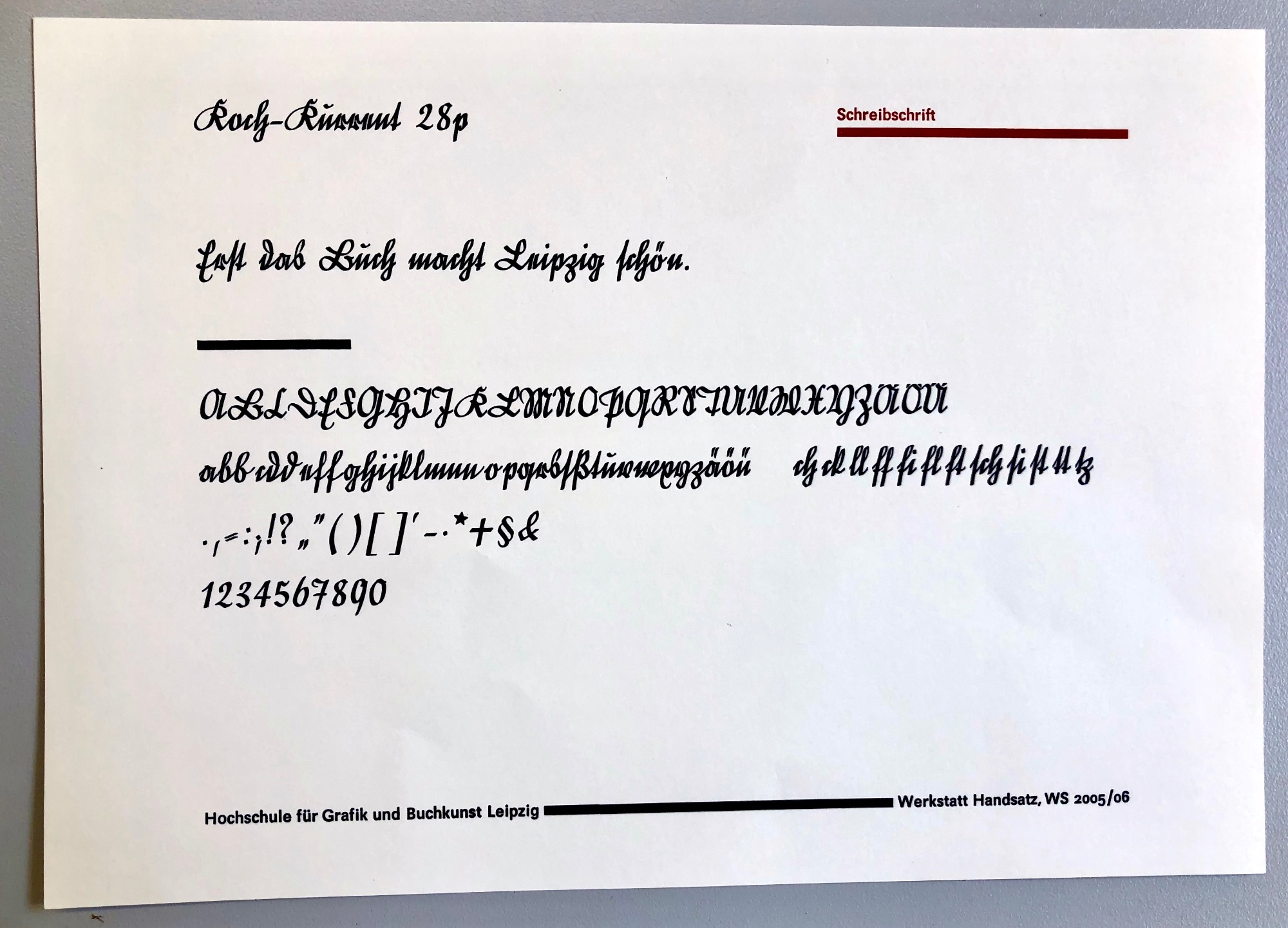
Nebenan: Kochs Kurrentschrift
Ich habe mir gerade Ralfs neuen Eintrag zur Koch-Kurrent von Rudolf Koch angesehen und dabei (freudig) festgestellt, wie viel Dynamik und »Charakter« die Schrift im Bleimuster [a] hat – und wie viel davon in der Digitalisierung [b] (wohl nur durch µ-weise Verschiebungen) verlorengegangen zu sein scheint. Das hatte für mich den Effekt, dass ich [a] sofort Lust aufs Kurrentlesen bekam, aber dann [b] – ruckzuck – auch wieder nicht.
Geht das nur mir so?
Naja, so eine schlampige Digitalisierung tut der Sache natürlich keinen Dienst. Die Verbindungen passen nicht; die Formen sind nurmehr durchgepaust. So geht alles Leben der Schrift verloren. Ein digitaler Abklatsch eben...
… umso mehr kann man wertschätzen, was für ein Kunsthandwerk doch die Matritzenschneiderei war.
Hallo. mein Name ist Iris Köhler. Ich bin gelernte Schriftsetzerin (wissenschaftlich-mathematischer Werksatz) und übe meinen Beruf mit Bleibuchstaben seit 49 Jahren aus. Acht Jahre bei INTERDRUCK und seit 41 Jahren in der Werkstatt Handsatz in der Hochschule für Grafik und Buchkunst Leipzig. Dies nur zur Vorgeschichte, damit Sie wissen, warum ich mich so gut auskenne.
Wir haben hier ein unserer Werkstatt 146 Bleischriften, u.a. auch die Koch-Kurrent. Ich liebe diese Schrift sehr. Hier ein Foto von dieser Schrift aus unserer Schriftmuster-Kartei.
Kleine Anmerkung: War es nicht eher so: Die Matrize wurde geschlagen, geschnitten hat der Stempelschneider die Patrize? Aber in der Tat, als Kunsthandwerk beeindruckend.
Der Großteil von Klingspor-Schriften entstanden wahrscheinlich im Zeugschnitt anstelle vom Stahlstempel. Die Patrizen waren wohl von Hand des Stempelschneiders geschnitten, jedoch war ein Metall verwendet, was weicher als Stahl war. Matrizen bzw. Matern waren dann nicht geschlagen. Stattdessen entstanden deren »Augen« im galvanischen Bad. Gelegentlich sind Matrizen bei Gebr. Klingspor auch direkt in Matrizen eingraviert worden, mittels einer Pantograf-Bohrmaschine. Rudolf Koch bzw. seines Sohnes Paul Koch (und Gustav Eichenauer etwas weniger wahrscheinlich) haben mehrere Schriften direkt in Stahl geschnitten. Das war damals schon eher alte Schule. David M. MacMillan haltet es für wahrscheinlich, dass Neuland zumindest zum Teil von Koch im Zeugschnitt geschnitten wurde. Kochs Arbeit an der Peter-Jessen-Schrift sowie an Marathon müsste tatsächlich in Stahl sein. Da die Koch-Kurrent nach dem Tod von Rudolf Koch herausgebracht wurde, weiß ich nicht, ob er selber an der Realisation der Schrift beteiligt war.